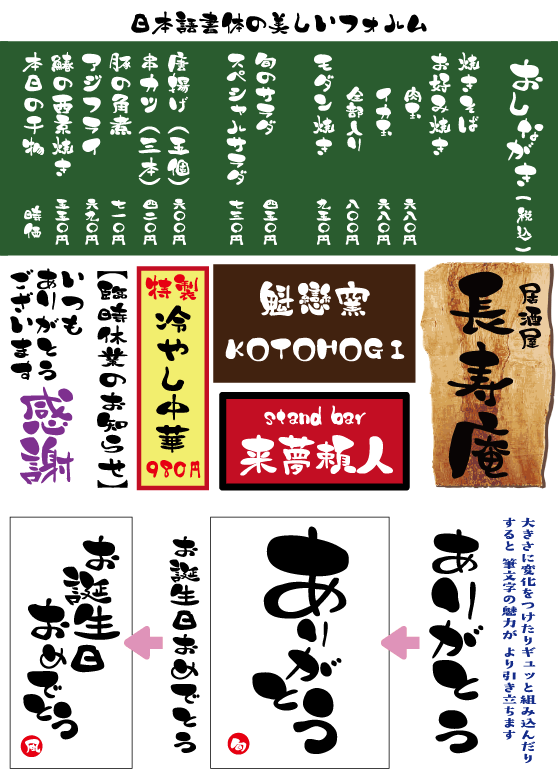
デザイン毛筆
AOI手描き筆文字
文字に命を宿す書画デザイナーの手仕事が、フォントになりました。
ロゴからキャッチコピーまで、置くだけで主役級の存在感を放ちます。伝統的な筆致と現代的な使いやすさが融合した魅せる文字。題字、看板、名刺、作品へのサイン、たいせつな文字に選んでいただきたいフォントです。
AOI手描き筆文字
全10,669文字
英字、数字、記号、ひらがな、カタカナ、教育漢字、常用漢字、第一水準、第二水準、IBM拡張文字、NEC特殊文字、ギリシア文字、キリル文字および第三水準の一部と第四水準の一部
文字に命を宿す書画デザイナーが、手描きの筆文字をデジタルデータに起こしてデザインするフォントブランド